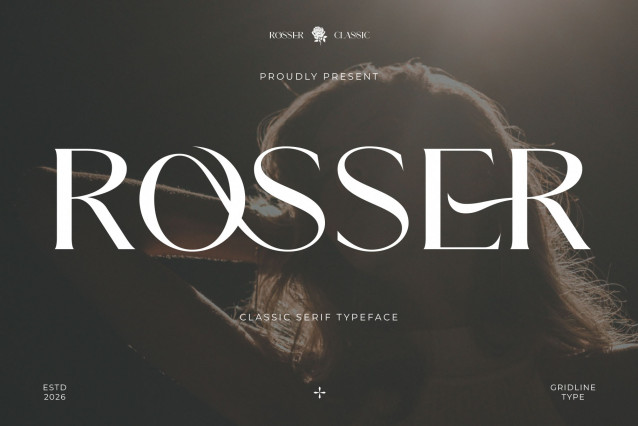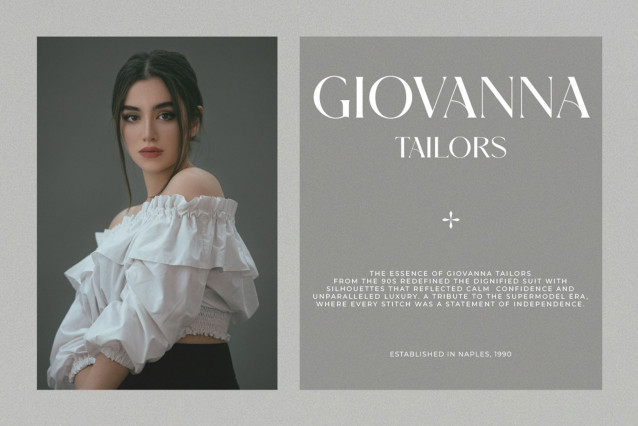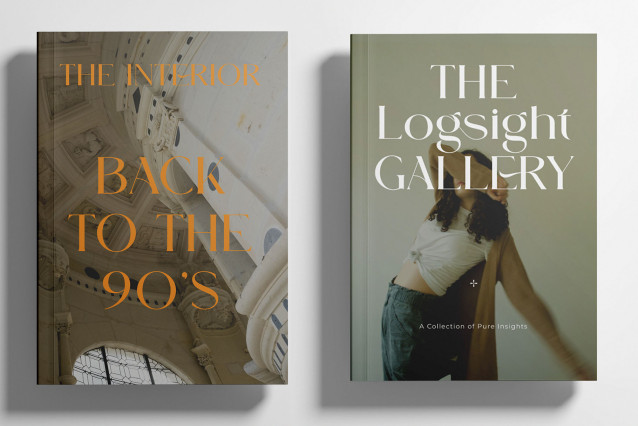
Rosser Font
Memperkenalkan **Rosser**, font Serif yang elegan, indah, dan modern. Dengan tampilan modern dan minimalisnya, Rosser menghadirkan gaya mewah, berkelas, dan bersih untuk proyek Anda seperti situs web, logo modern, identitas merek, kutipan media sosial, alat tulis pernikahan, majalah, dan banyak lagi!
Rosser menampilkan huruf kapital A hingga Z yang unik dan berkelas, serta dilengkapi dengan alternatif unik yang menjadikan Rosser font indah yang dapat disesuaikan untuk berbagai proyek dan pekerjaan yang Anda inginkan.